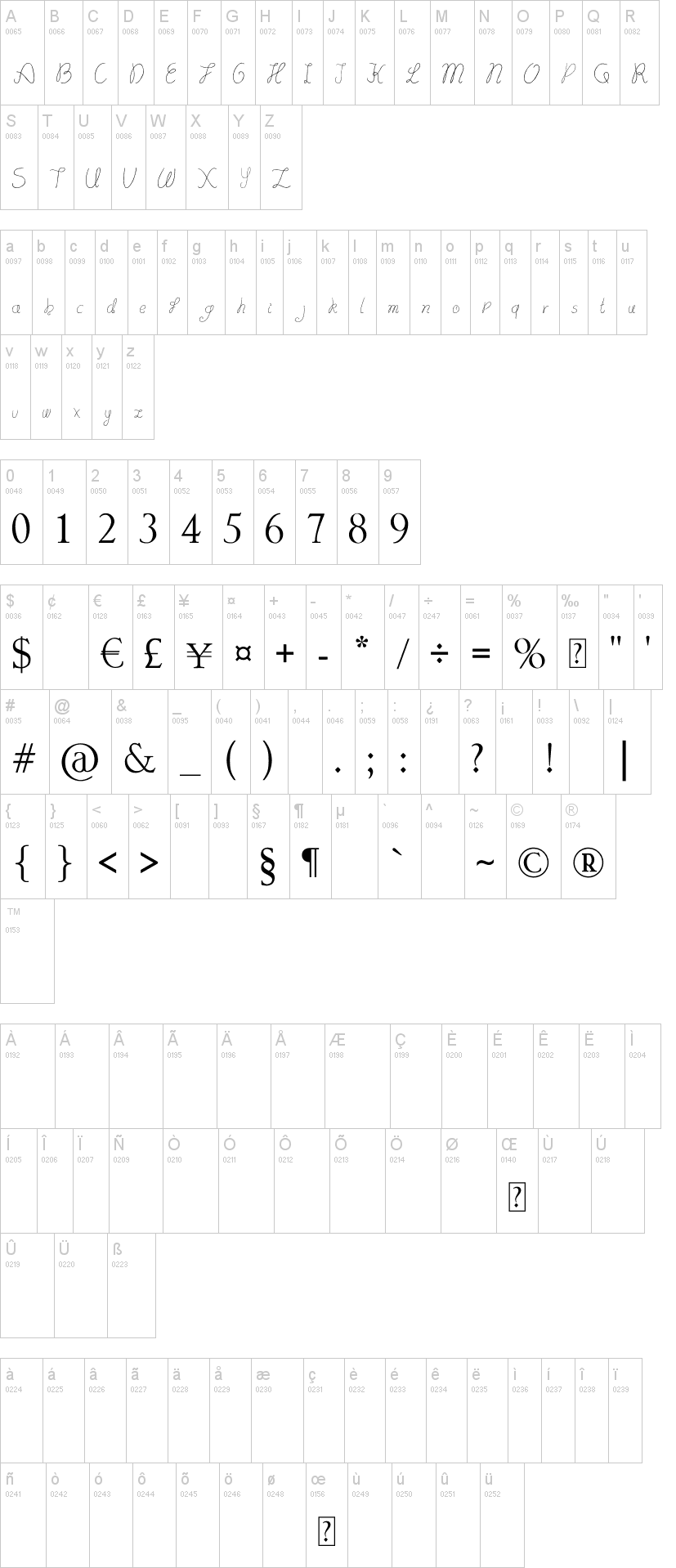
Lydeke Handwrithing
? Lydeke Handwrithing 字体是一款细腻柔和的手写字体,具有优雅的曲线和轻柔的笔触,是一款精致的欧洲风格字体。它的字符设计融入了许多欧洲文化的特点,拥有温柔的笔画,柔和的曲线,给人一种温暖的感觉。它也具有较强的可读性,可以帮助您更好地表达您的想法。
Lydeke Handwrithing是一款非常不错的手写艺术字体,具有很好的视觉感,适合于文化类的宣传设计、商业类品牌的广告和产品包装设计以及个性化文字排版等较多场景。